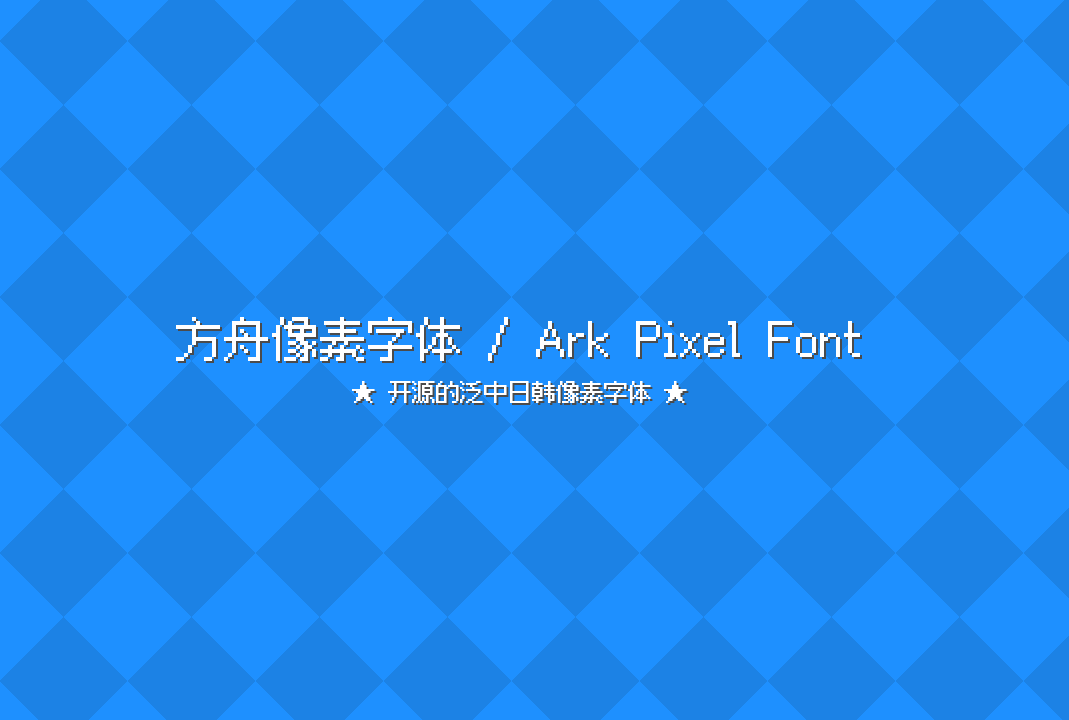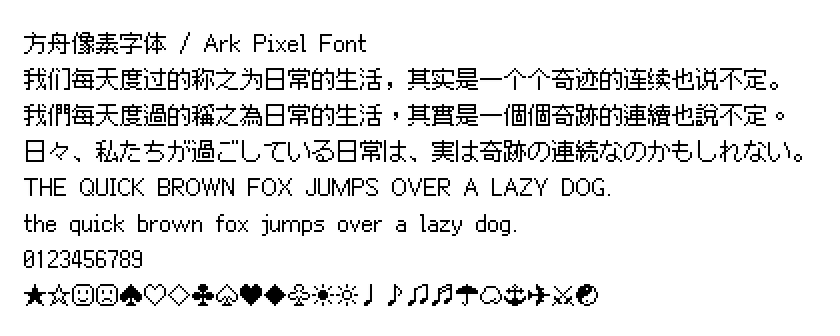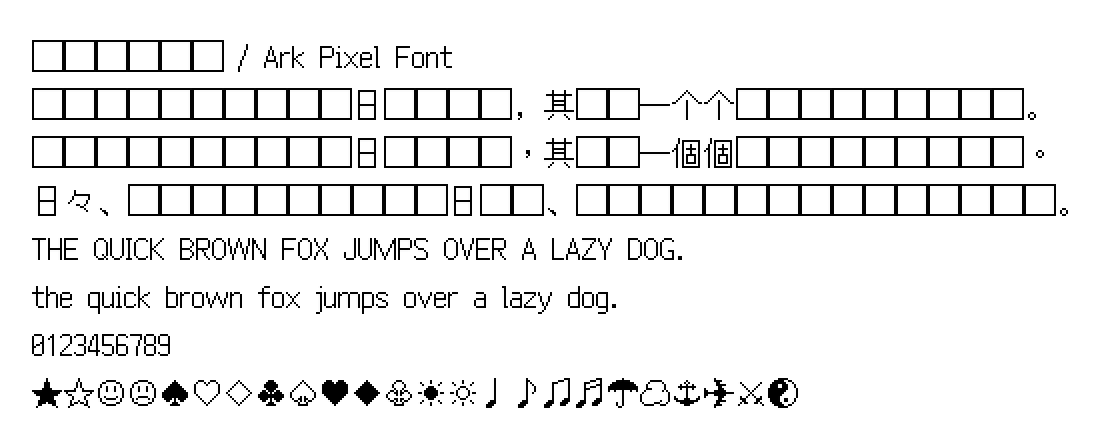
方舟像素字体 / Ark Pixel Font 是一款开源的泛中日韩像素字体。支持 10、12 和 16 像素。目标是为游戏开发提供一套可用于正文的开箱即用的像素字体解决方案。该项目提供了全部的字形源文件,也提供了构建字体所需要的完整程序。
方舟像素字体 / Ark Pixel Font 目前还处于开发阶段,所有尺寸仍然缺少大量汉字。其中 12 像素为主要开发目标。10、16 像素为实验性质。
覆盖范围如下(截止本文发布日期):
尺寸西文字母汉字日语假名谚文音节各种符号
10px覆盖基础拉丁、西里尔、希腊与科普特偶尔施工,目前极少完成未开始覆盖常用
12px覆盖基础拉丁、西里尔、希腊与科普特施工中,目前整体 1 万字左右完成未开始覆盖常用
16px覆盖基础拉丁、西里尔、希腊与科普特未开始,目前极少进行中未开始覆盖常用
该字体目前支持「等宽」和「常规比例」两种模式。
支持语种:
后缀latinzh_cnzh_hkzh_twzh_trjako
语言拉丁语中文-中国大陆中文-香港特别行政区中文-台湾地区中文-传统印刷日语朝鲜语
10 像素 示例文本(图片)
方舟像素字体(Ark Pixel Font)10 像素 示例文本(图片)
12 像素 示例文本(图片)
方舟像素字体(Ark Pixel Font)12 像素 示例文本(图片)
16 像素 示例文本(图片)
方舟像素字体(Ark Pixel Font)16 像素 示例文本(图片)